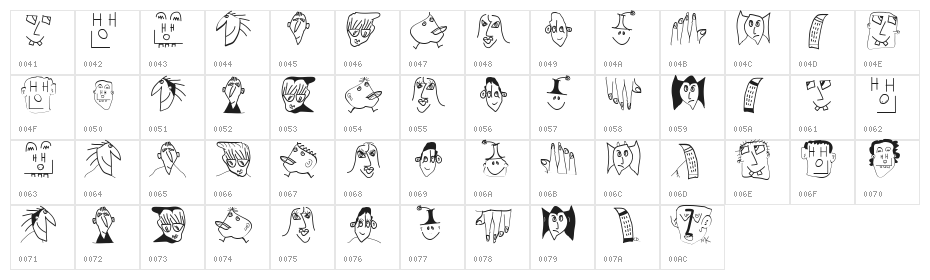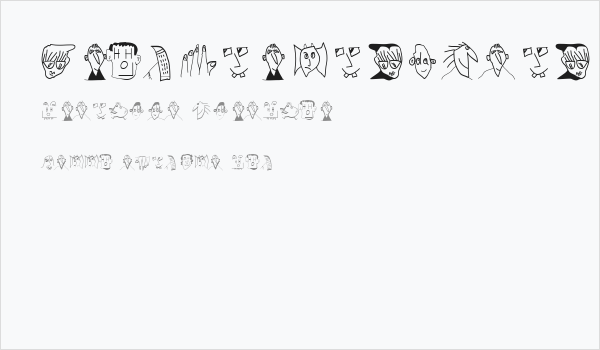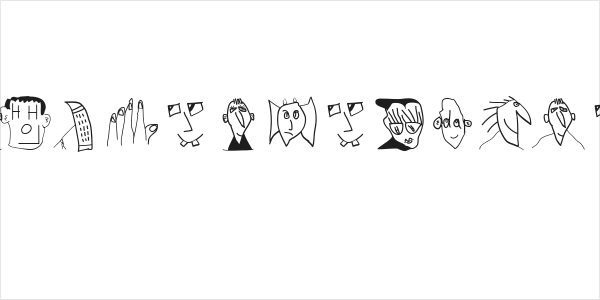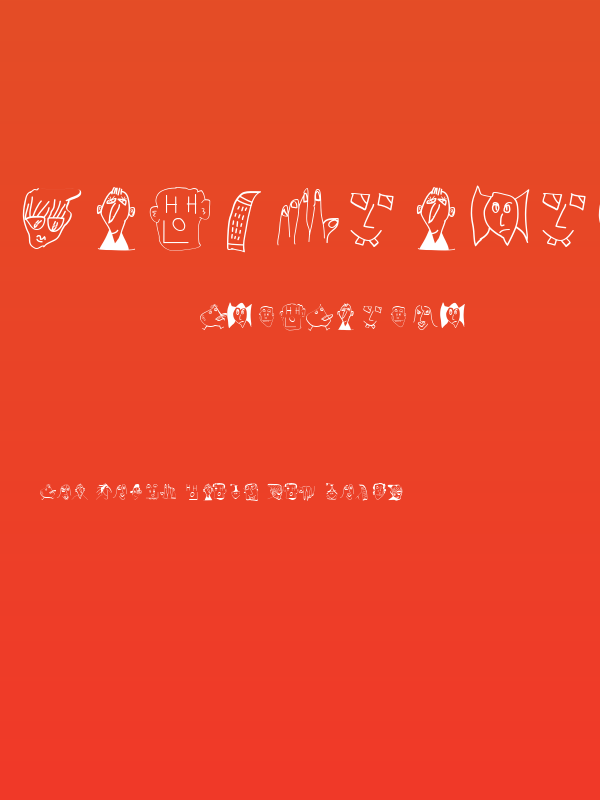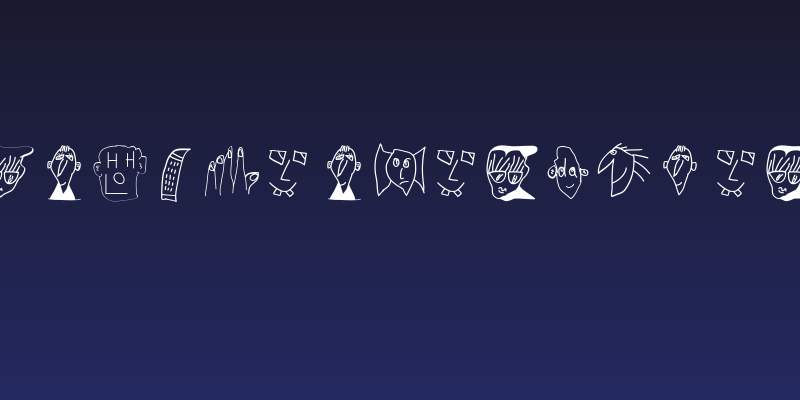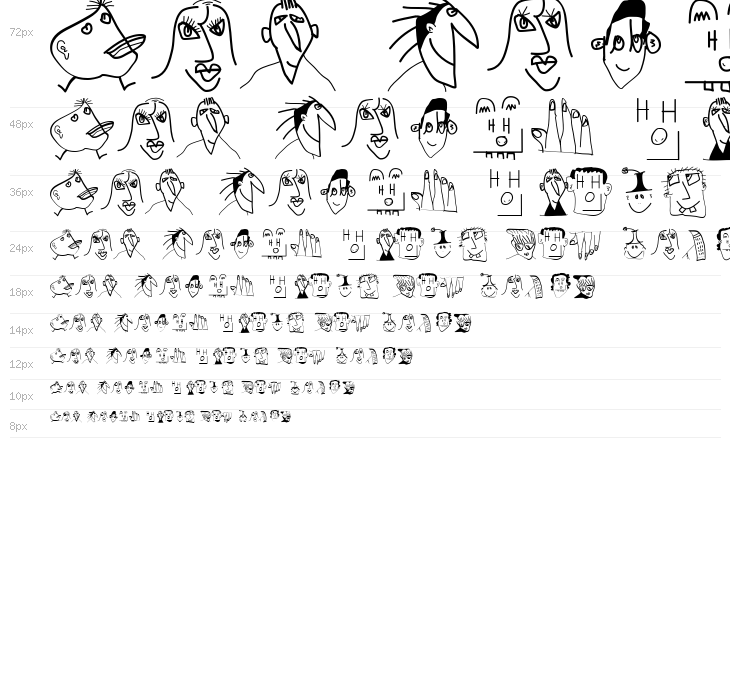
FromKarlasIdeas Font
| Estilo general | Artistic, Whimsical, Creative |
| Caso de uso | Artistic designs, Posters, Creative displays |
| Proyectos propuestos | Ideal for creative projects such as posters, album covers, art installations, or any design requiring a playful and artistic touch. |